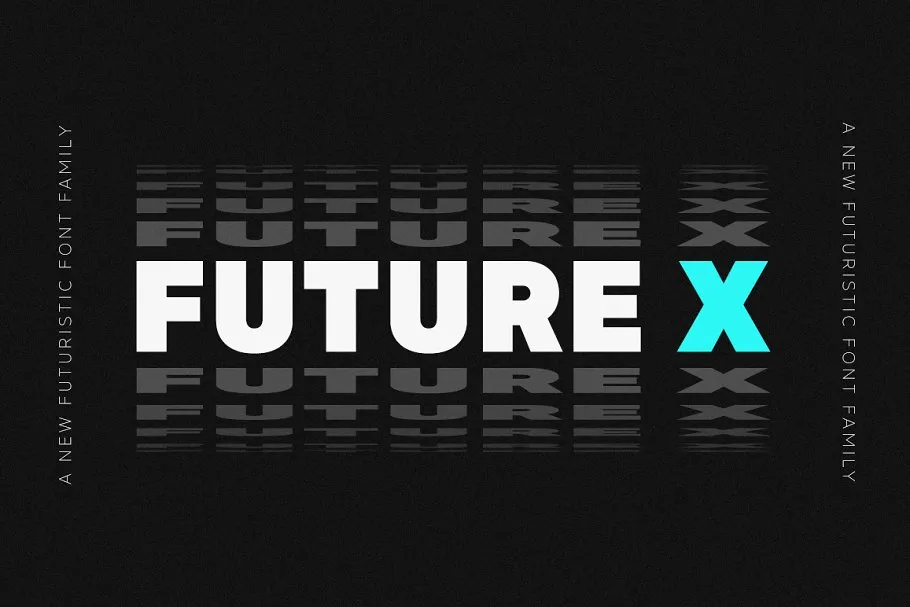
MADE Future X Font Family – Fonte Grátis
MADE Future X Font Family – Download Grátis
MADE Future X Font Family
Olá font lovers! Estamos muito empolgados com a introdução da Future X Font! Ela é projetada pelo MadeType e está disponível para compartilhamento. A Family Futura X suporta várias letras multilinguas. Ideal para uma vasta gama de projetos, incluindo logotipos, marcações, revistas, citações, cabeçalhos de blog, cartazes e anúncios. E o Future X HEADER é perfeito para headlines, cabeçalhos de blogs, cartazes, jornais, logotipos, design de livros, posters musicais e muito mais. O Future X HEADER também oferece alternativas de letras ativa através da tecla ‘Caps Lock’, tornando-o ainda mais versátil. Estamos ansiosos para que você explore e descubra como a Family Futura X pode potencializar seus projetos!